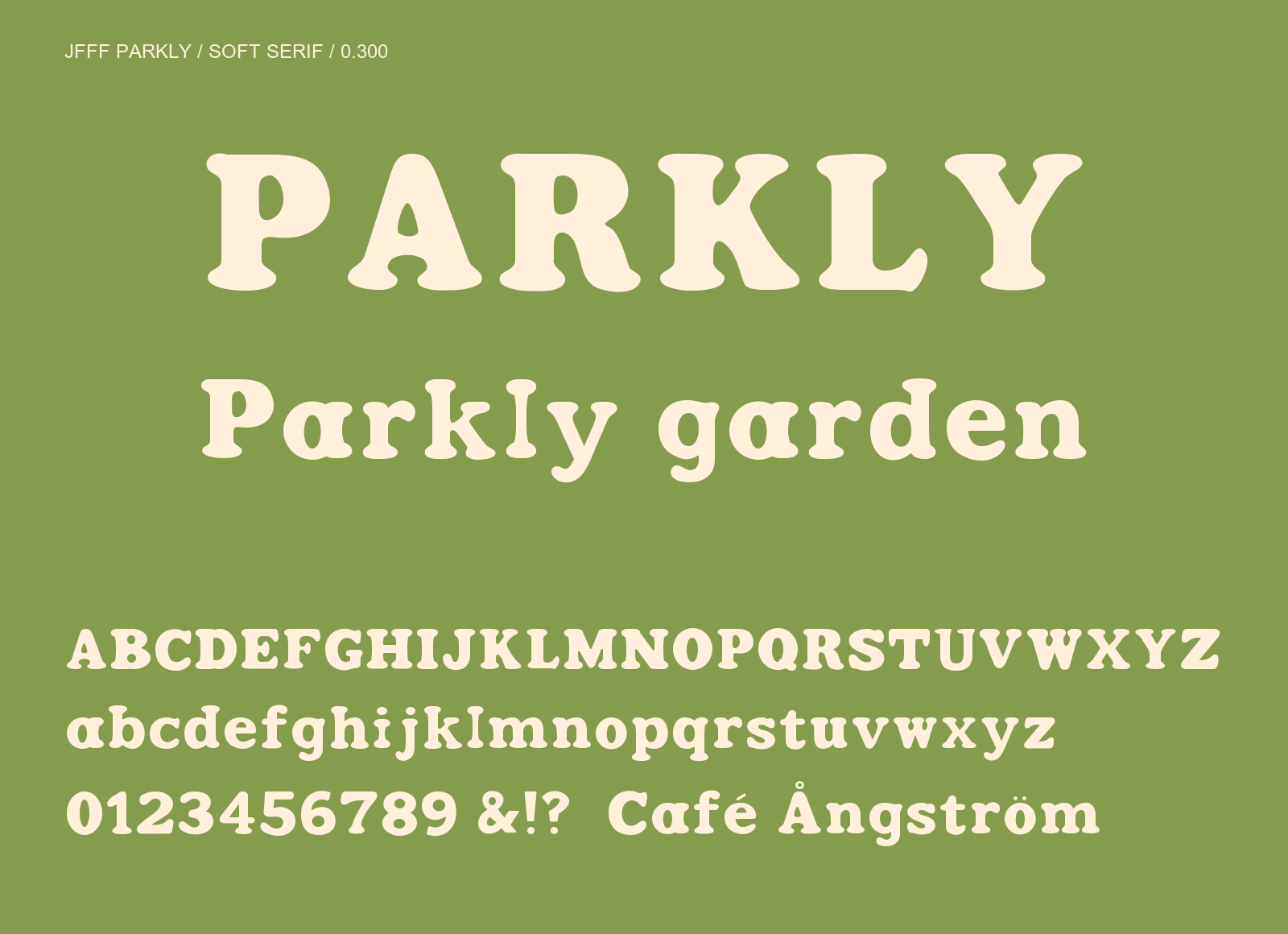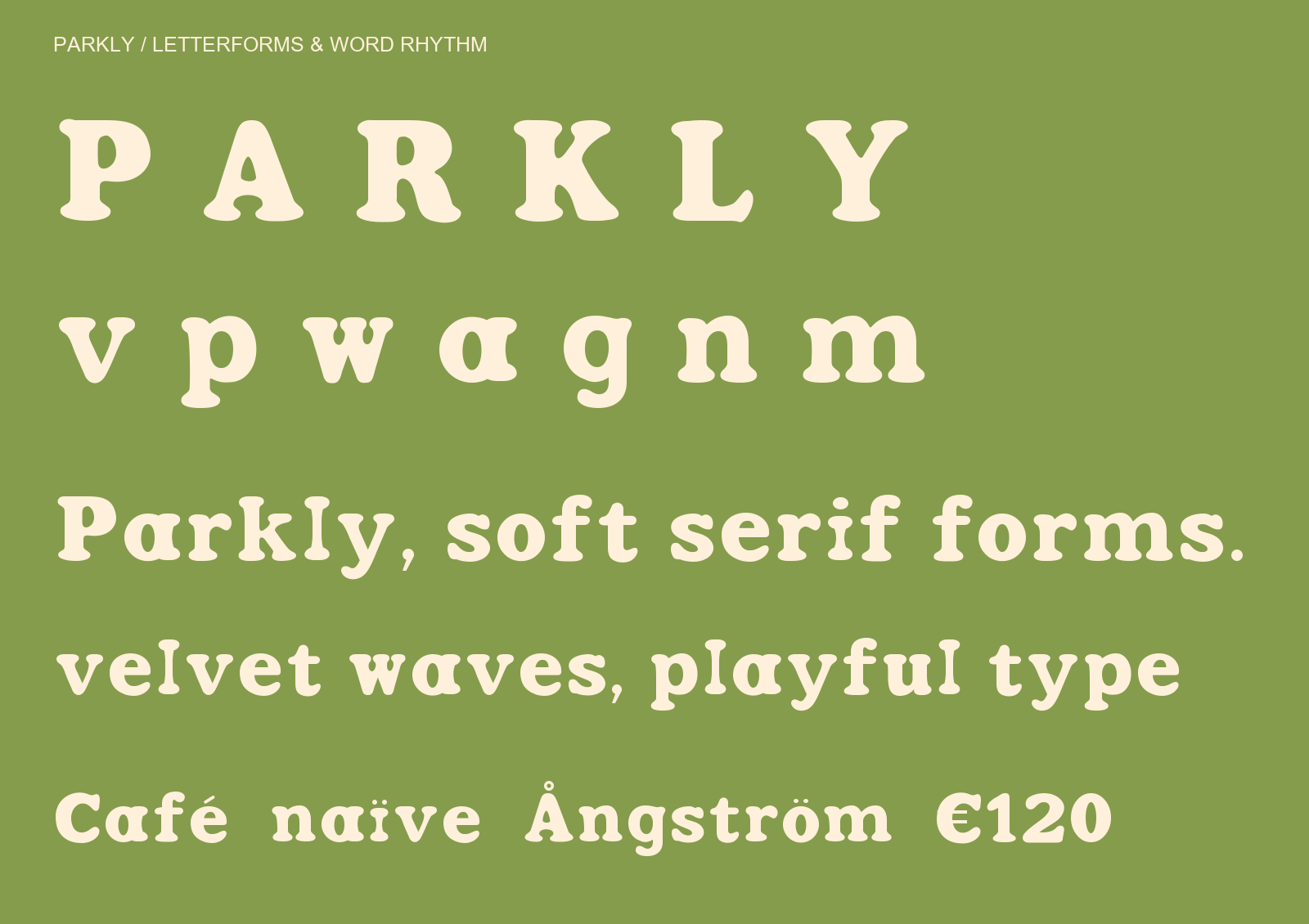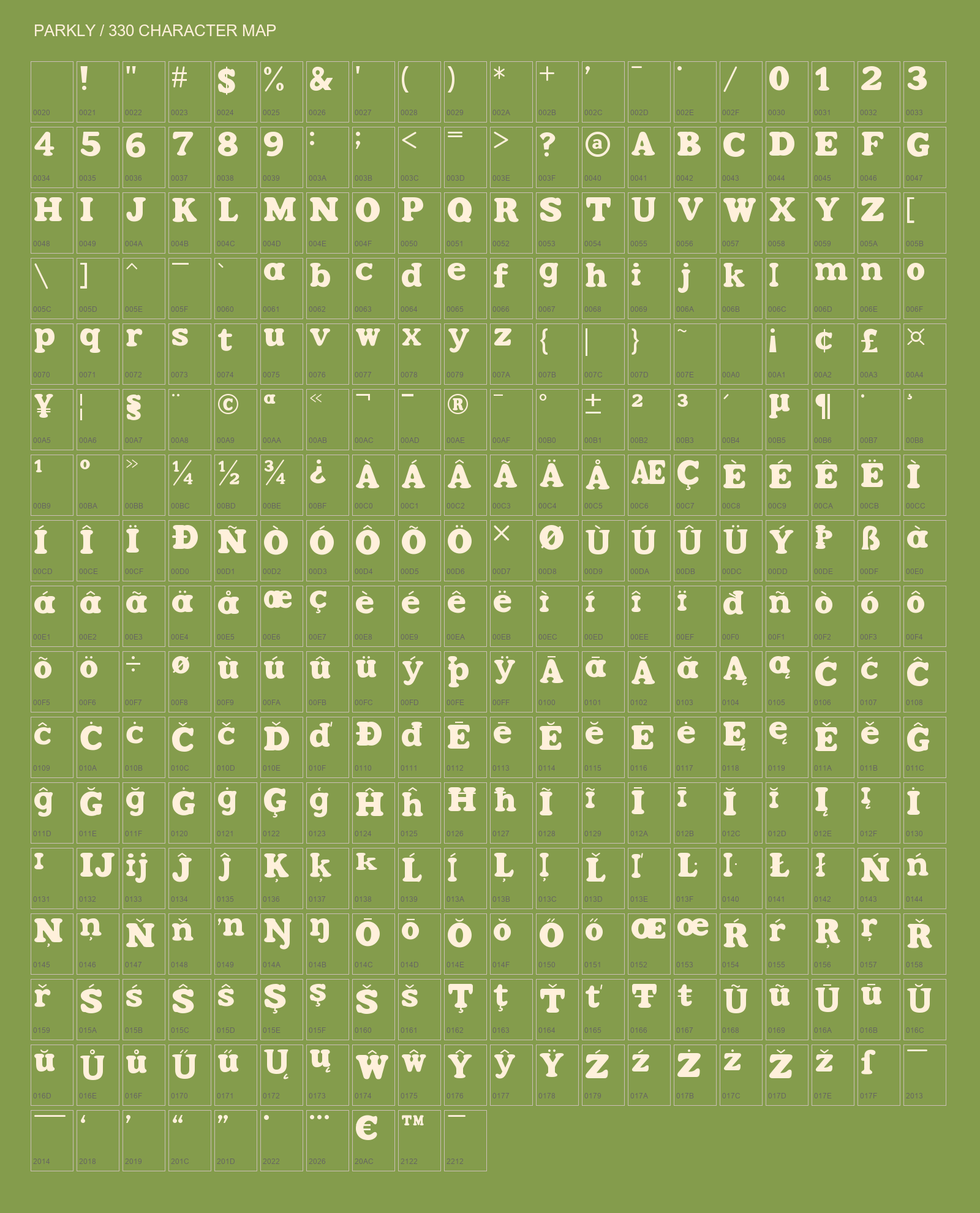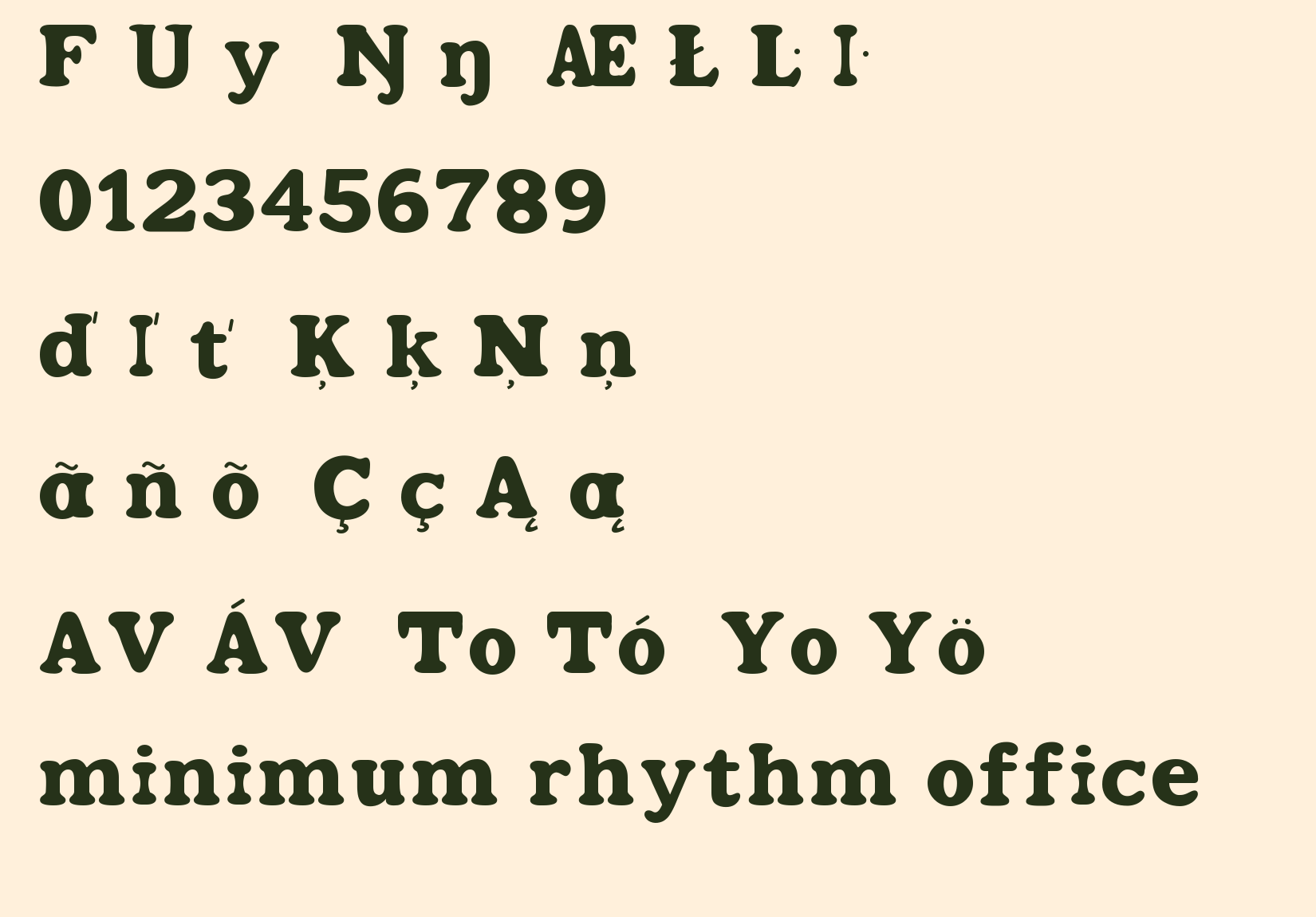
Free high-contrast serif font
Latin only. No Hangul.
Parkly는 부풀어 오른 둥근 세리프와 좁은 타원형 속공간, 유연하게 휘어지는 다리가 특징인 굵은 디스플레이 서체입니다. P·A·R·K·L·Y의 개성을 중심으로 따뜻한 빈티지 분위기를 담았습니다. Regular 0.300 · 라틴 330자(공백 포함). 영문 대소문자, 숫자, 확장 라틴 악센트 및 기호를 지원하며 한글은 포함하지 않습니다. TTF와 WOFF2를 하나의 ZIP으로 제공합니다. SIL Open Font License 1.1에 따라 무료로 사용할 수 있습니다. 0.300에서는 F와 Ŋ/ŋ, 숫자와 소문자 y, 접합부, 악센트 위치 및 자간을 다듬었습니다. 48px 이상 제목·포스터·패키지용으로 권장합니다. 소문자와 확장 문자는 디자인 해석이며 기존 자체 제작 골격을 포함합니다. 비공백 출력 누락과 세로 메트릭, 주요 확대 표본을 확인했으며 모든 문자쌍 및 운영체제별 검수까지 완료한 것은 아닙니다.